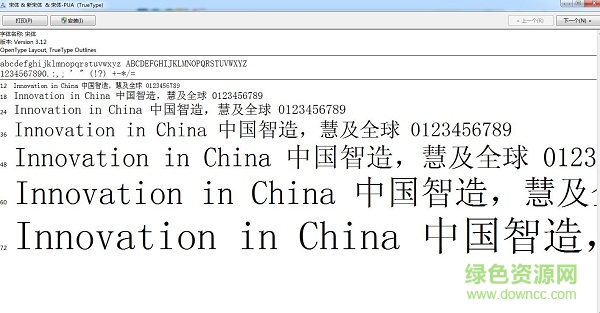
simsun-pua字體是一款支持中英文輸入的宋體字體,這款字體的中文輸入和simsun一樣,外觀經(jīng)典,結(jié)構(gòu)標(biāo)準(zhǔn),但是英文采用了過(guò)渡型襯線(xiàn)字體,字符輸入更好看,喜歡的朋友歡迎免費(fèi)下載!
宋體字體介紹
Sim是simplified的縮寫(xiě),亦簡(jiǎn)體的意思,SimSun就是簡(jiǎn)宋的意思,目前宋體、黑體、仿宋體和楷體成為漢字印刷的主要四種字體?!杆误w」是一類(lèi)字體的總稱(chēng),有很多字體都屬于這個(gè)范疇。